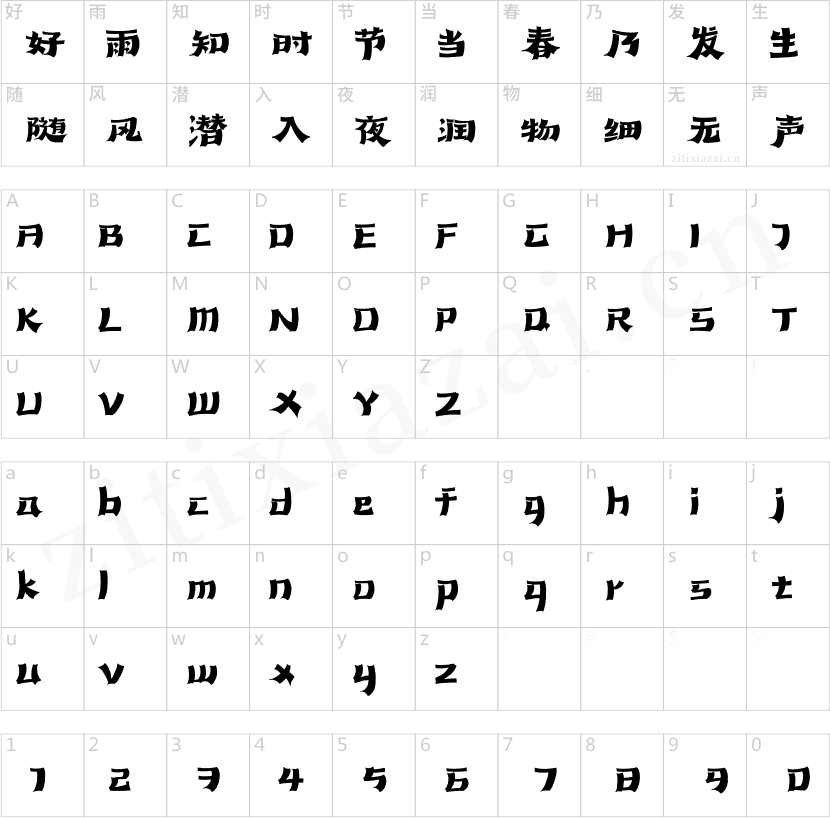
汉仪本默呐喊
汉仪本默呐喊,这款字体结构工整、笔画清晰,兼顾美观与易读性,适用于标题、正文、海报、包装、LOGO 等多种场景。字形优雅稳定,风格百搭耐看,适配日常排版与创意设计,让文字呈现更舒适、更具质感。汉仪本默呐喊一笔一画,皆是细节,以均衡的比例、流畅的线条打造舒适视觉体验,字形端正大气,风格简约现代。无论是商业设计、品牌宣传还是日常排版,都能轻松驾驭,让文字更有格调与力量。汉仪本默呐喊字体下载。
• 字体说明:汉仪本默呐喊是汉仪字库签约作者本默(王琪)创作的一款风格怪诞的手写字体,夸张而极具装饰性。这款字体源于作者在一次海报创作中的偶然尝试,是在宋体和黑体的基础上进行再次创作的美术字体,整体以扁平化为基调,结合板书的设计呈现,具有视觉冲击力和极高的辨识度,夺人眼球,适合作为标题字体满足多种应用场景。